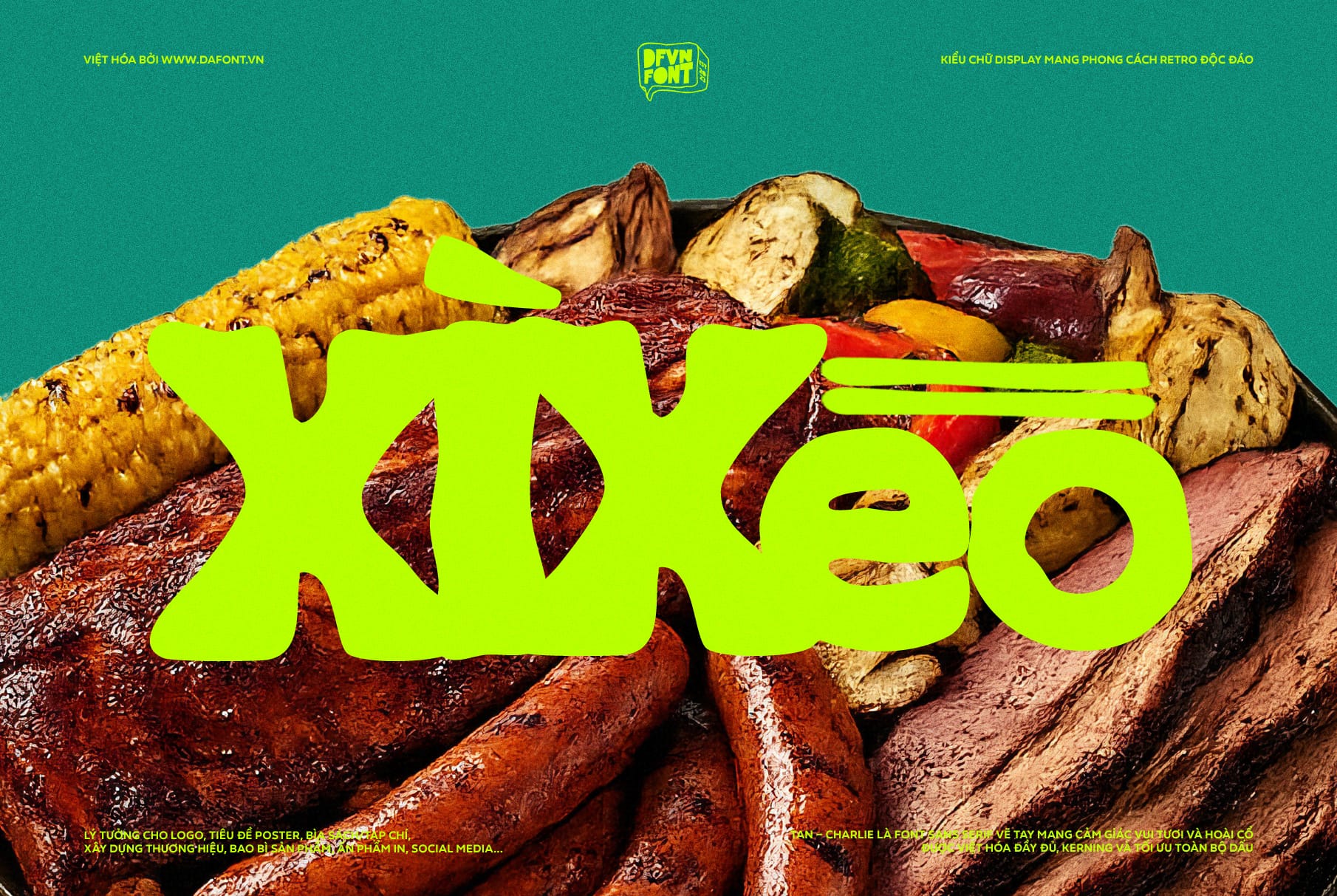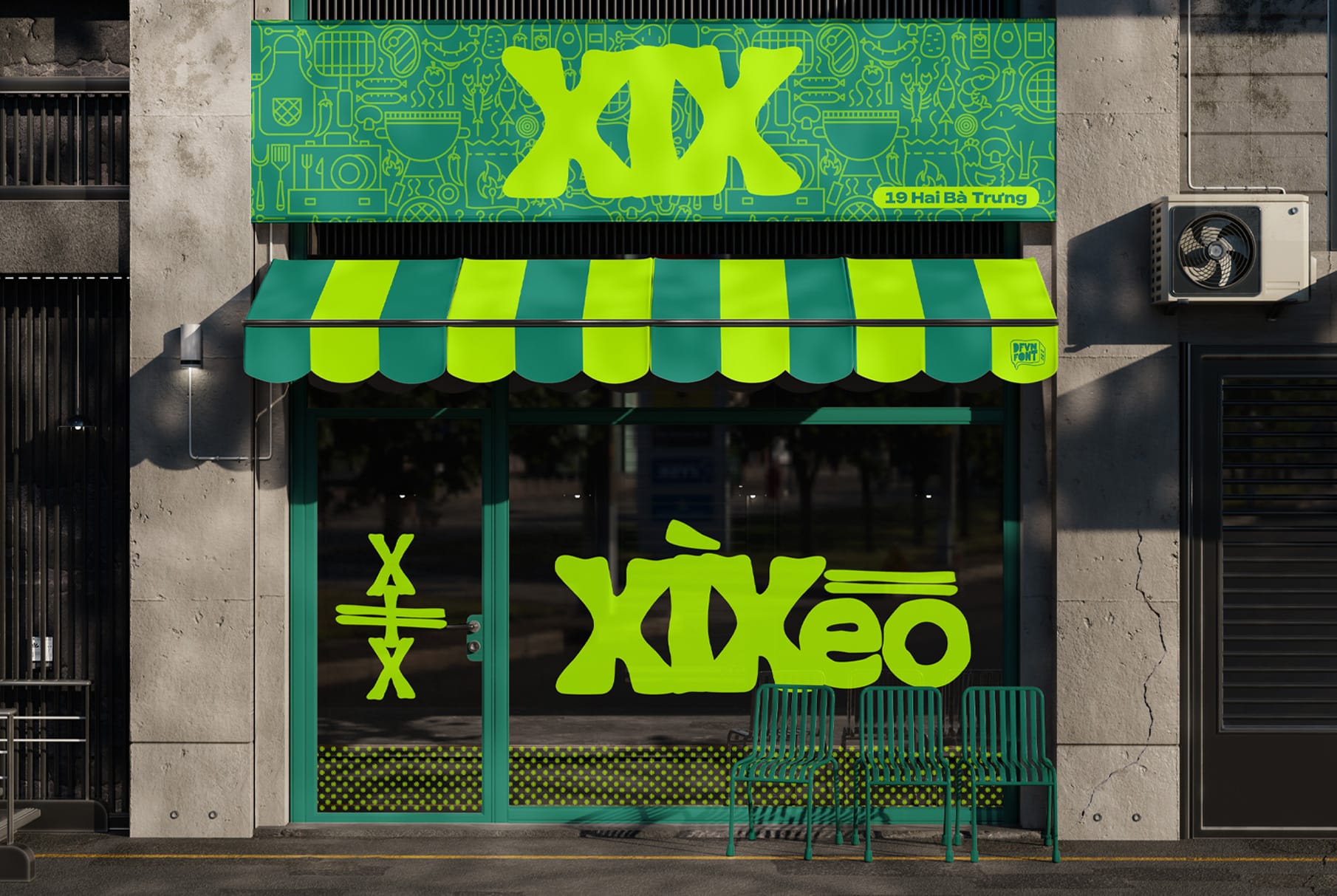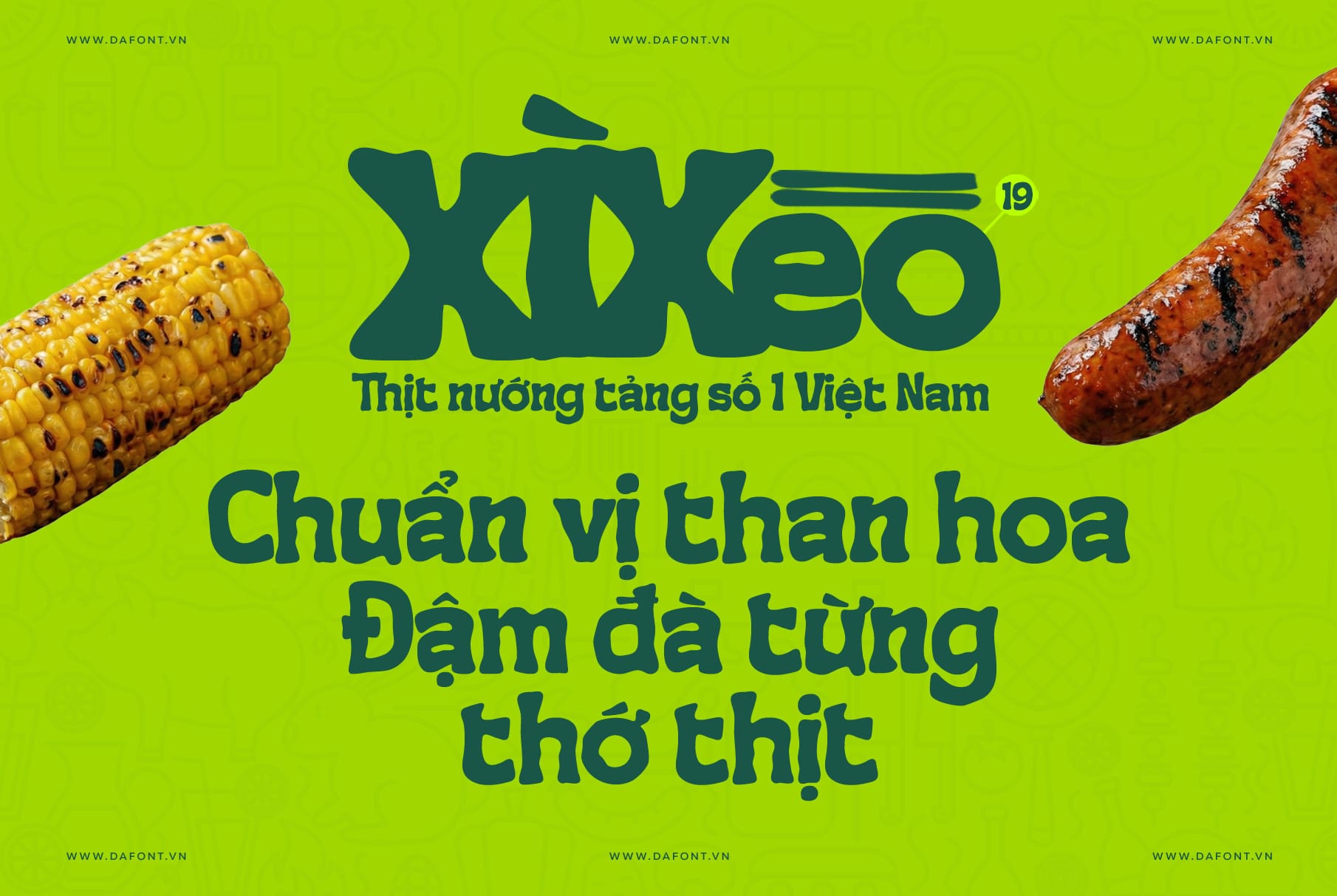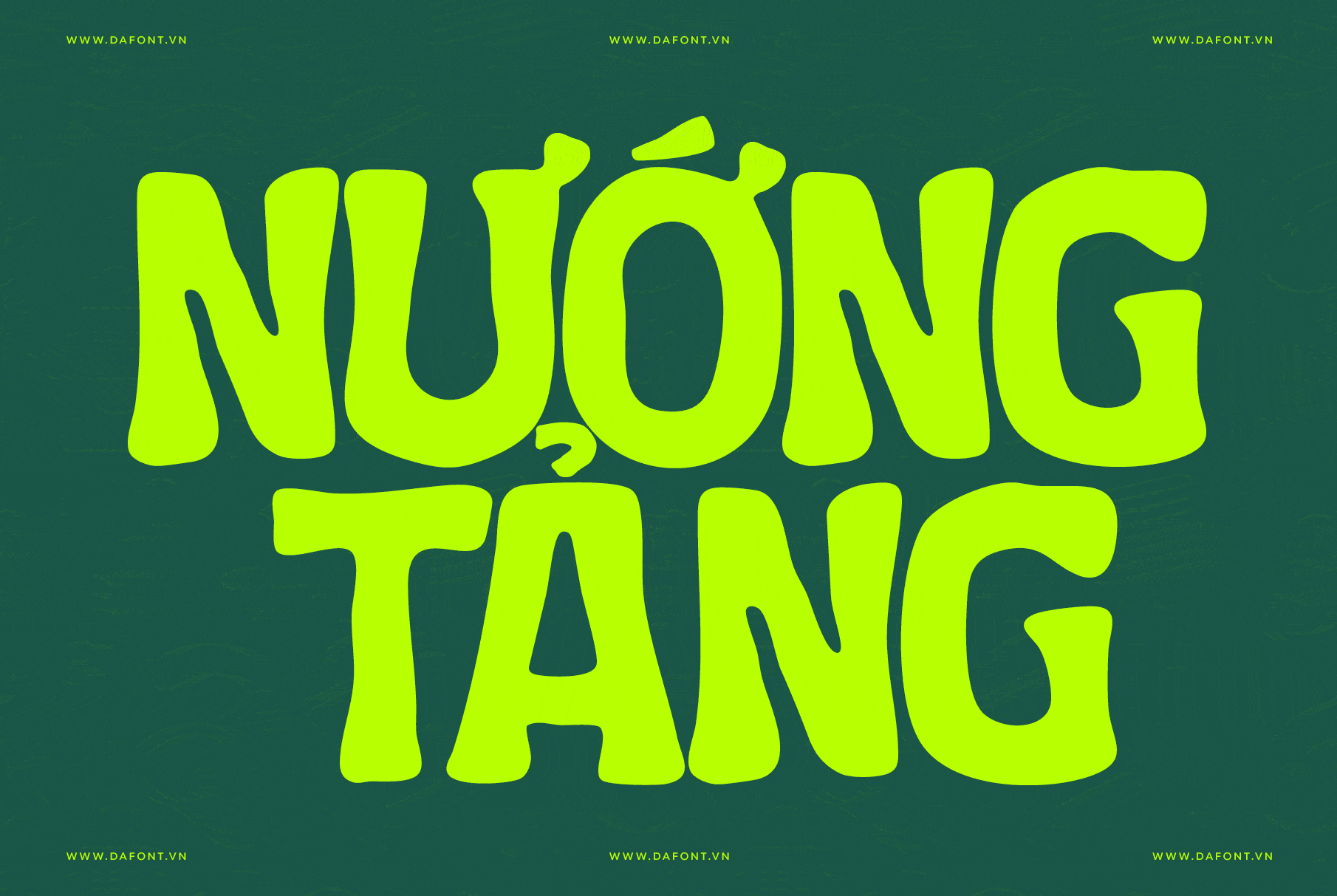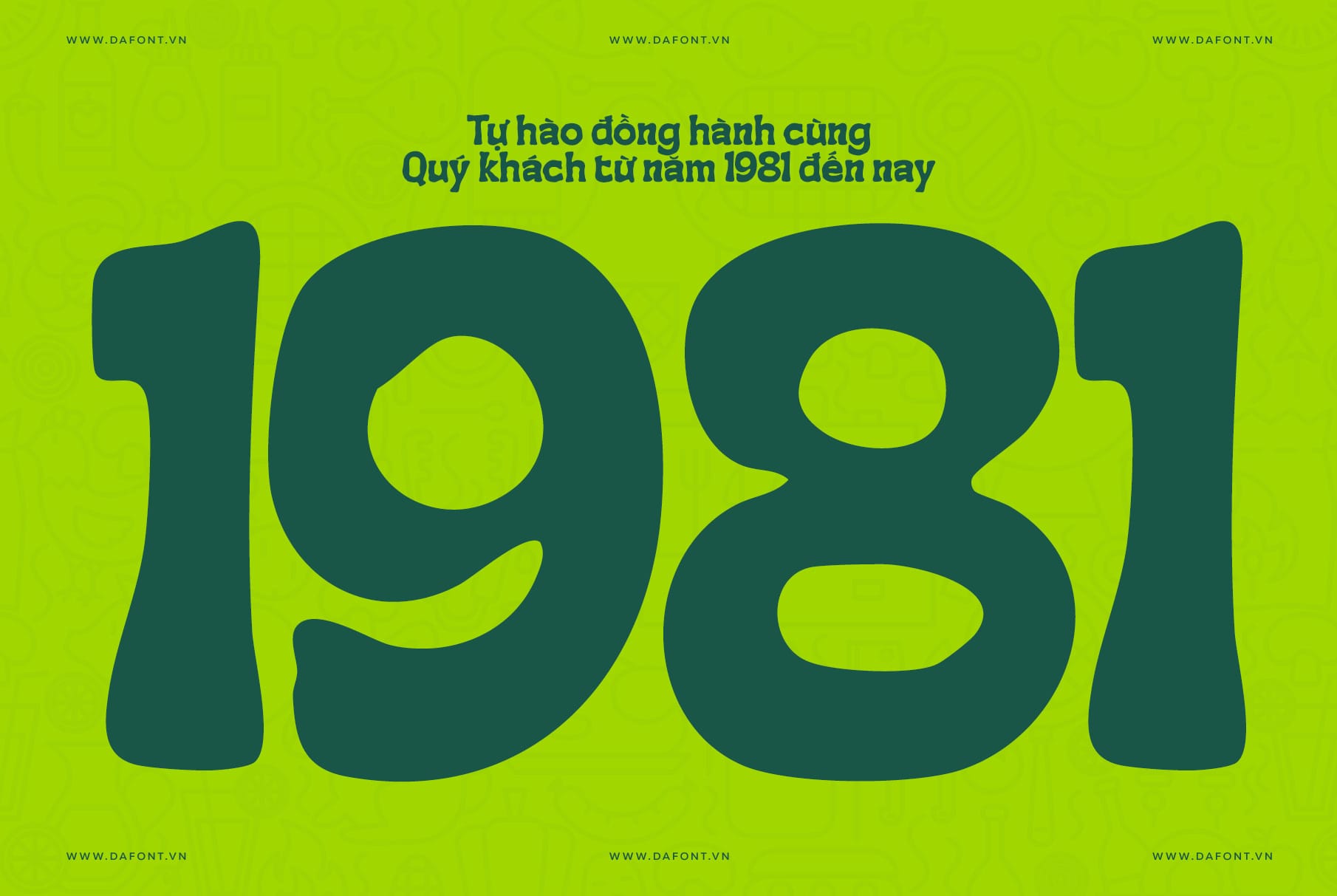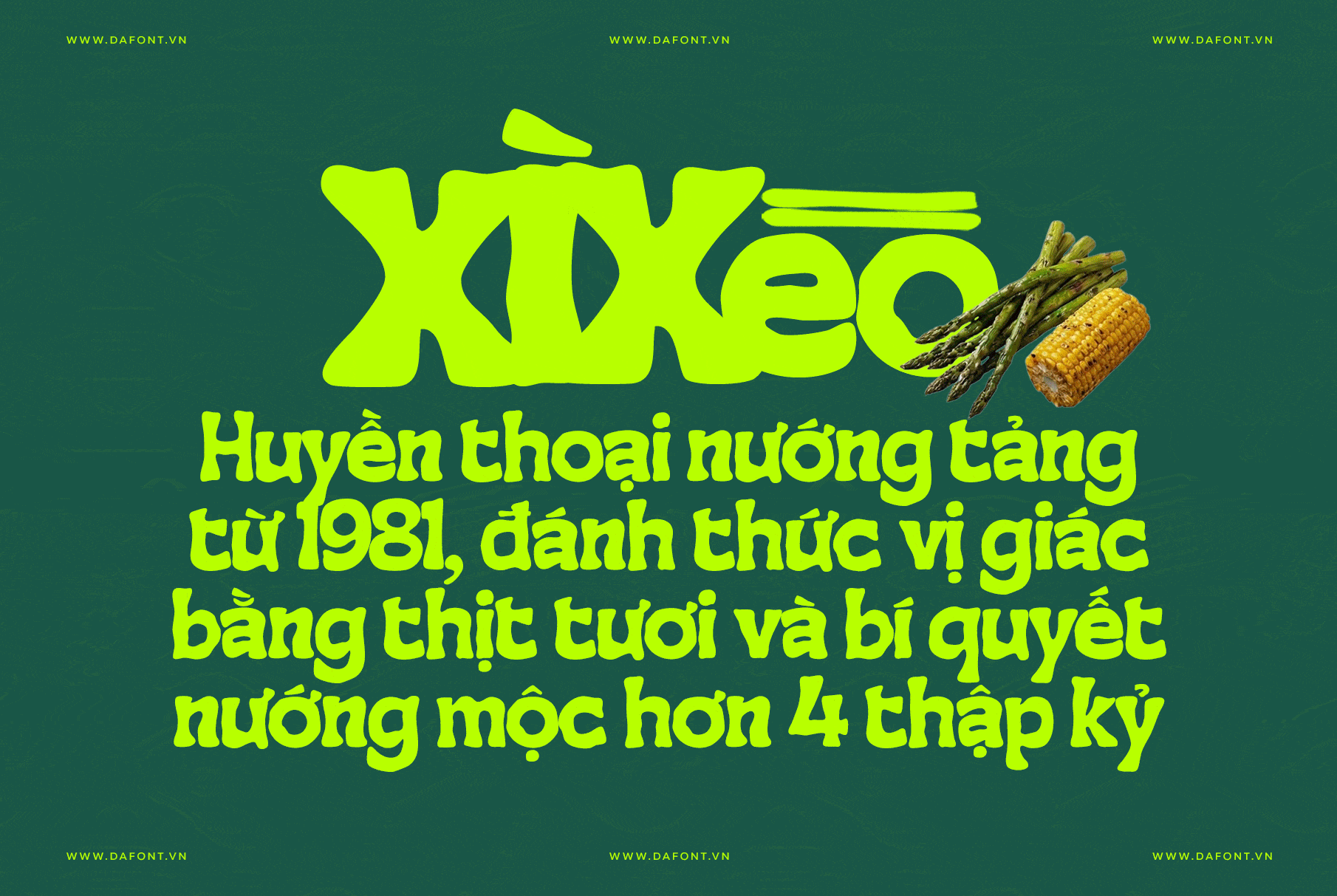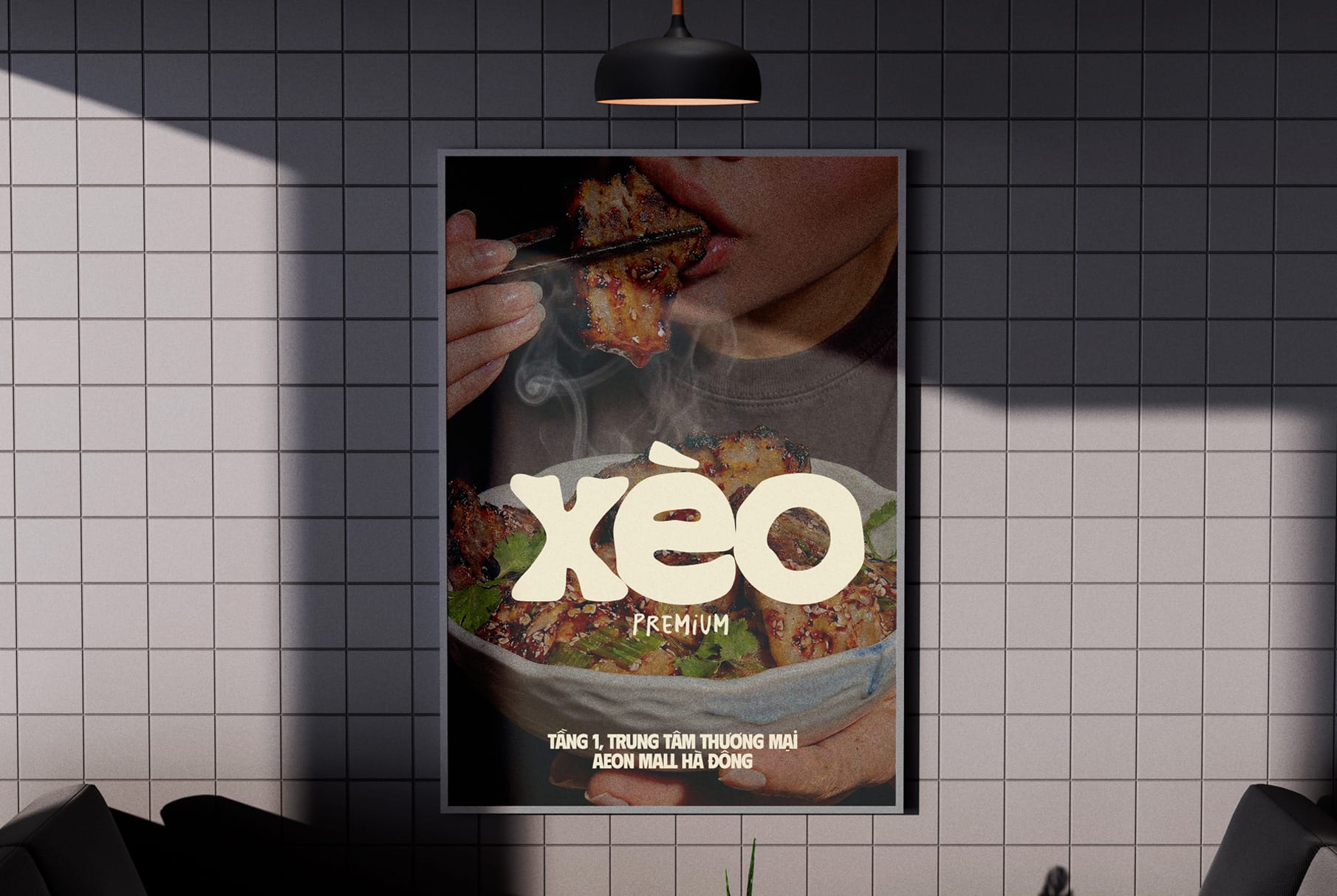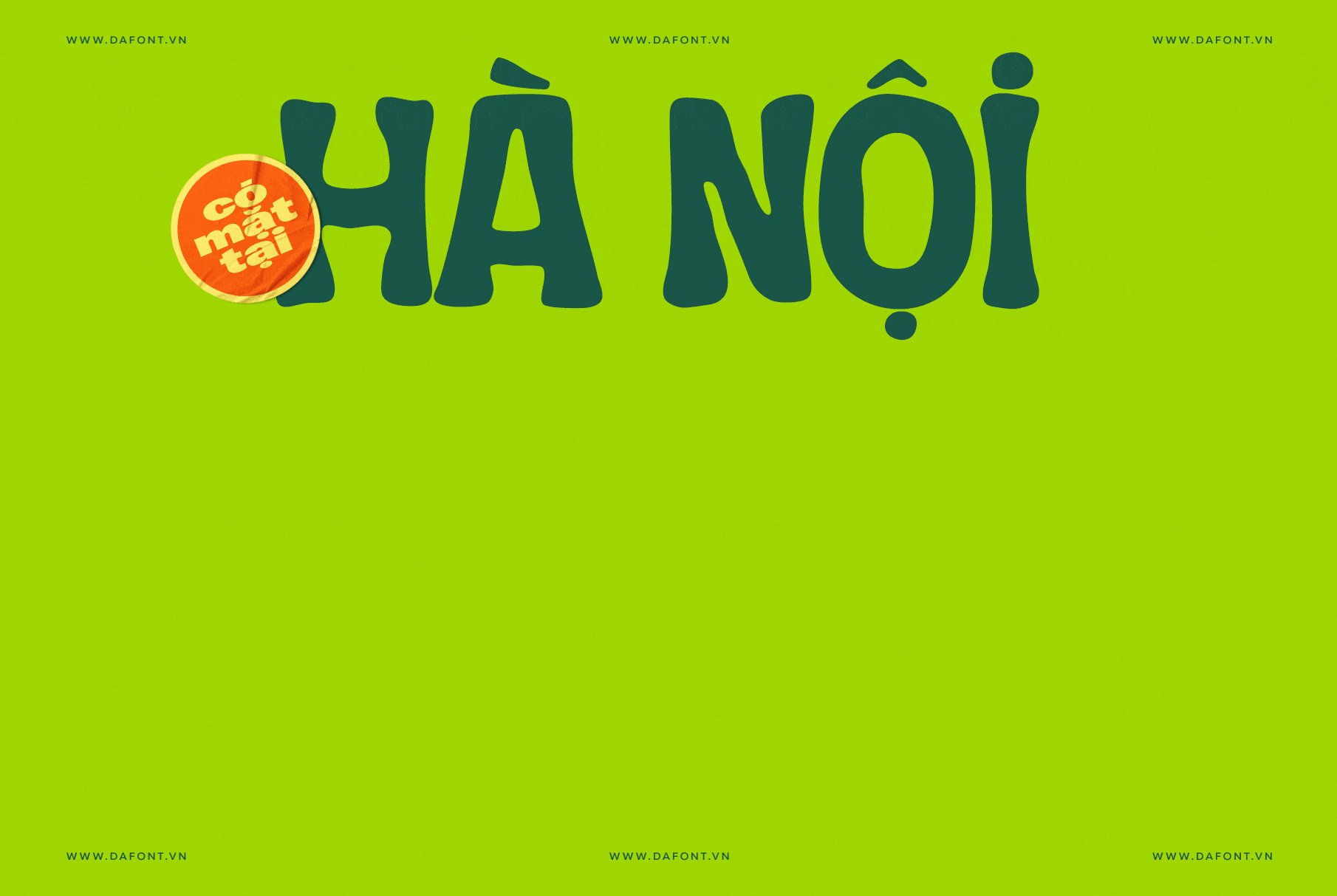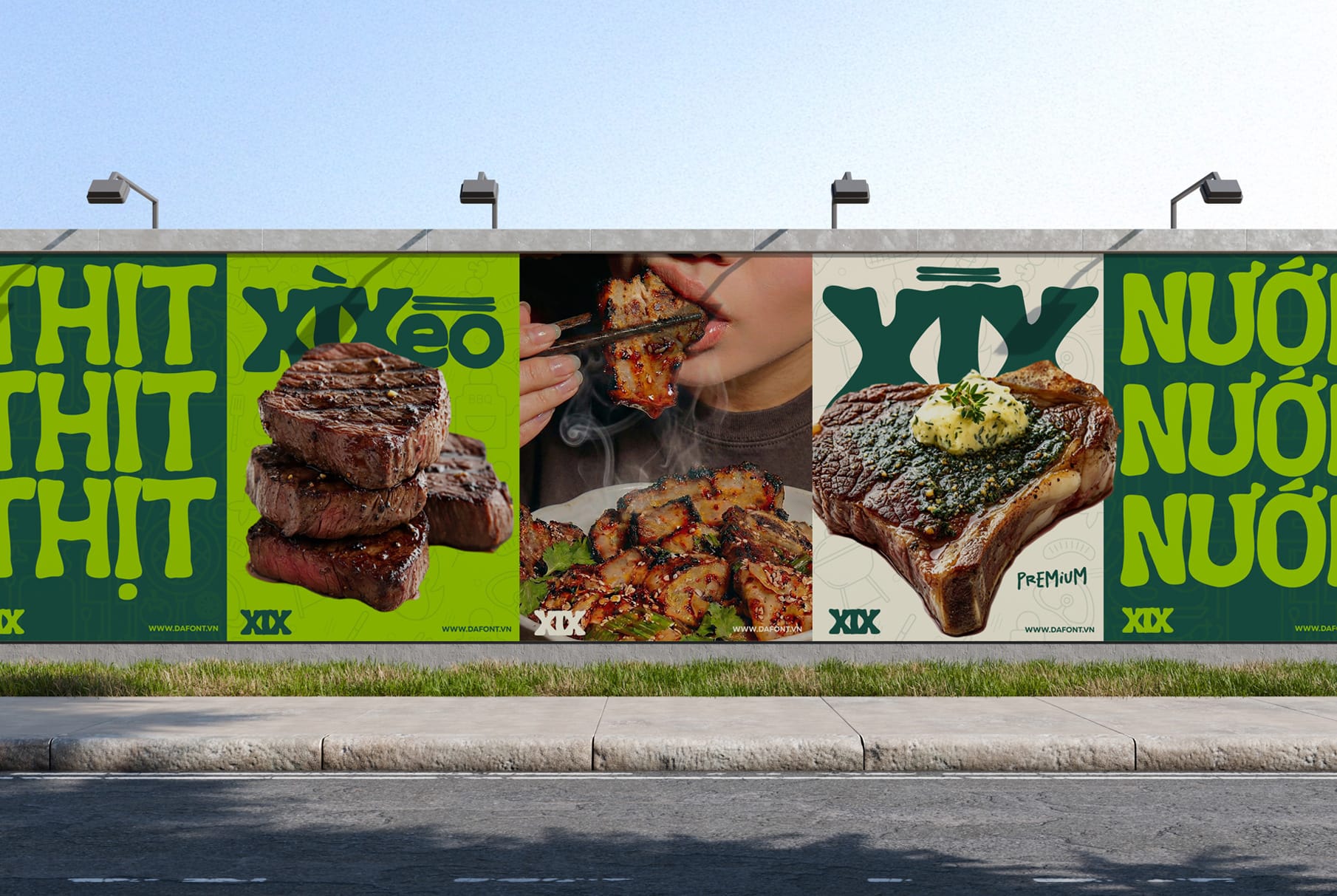
Trong vài năm trở lại đây, các font handwritten, retro và mang hơi hướng thủ công đang trở lại cực kỳ mạnh mẽ trong thiết kế thương hiệu. Giữa “rừng” font chữ đó, DFVN TAN – CHARLIE nổi bật như một lựa chọn độc đáo: vừa vui tươi, ấm áp, lại vừa hoài cổ nhưng không hề cũ kỹ.
Các đường nét của TAN – CHARLIE được thiết kế có chủ ý hơi lệch, không đồng đều như các font sans serif hiện đại. Chính cảm giác “không hoàn hảo” này tạo ra sự thủ công độc đáo, khiến text nhìn như được ai đó vẽ tay nhưng vẫn đủ chuyên nghiệp để đưa vào hầu hết các thiết kế.
Đặc điểm nổi bật DFVN TAN – CHARLIE
Tại sao TAN – CHARLIE lại được yêu thích đến vậy? Dưới đây là những lý do khiến font chữ này trở nên đặc biệt:
Đường nét vẽ tay tinh tế
TAN – CHARLIE không phải kiểu “chữ viết tay cẩu thả”, mà là hand-drawn sans serif có kiểm soát. Mỗi chữ cái đều được cân chỉnh về rhythm, weight và khoảng cách, đảm bảo khi ghép thành từ/ câu vẫn giữ được nhịp điệu thị giác dễ chịu.
- Nét chữ hơi bo tròn, không quá sắc cạnh
- Độ dày nét ổn định, dễ đọc khi dùng làm tiêu đề
- Tạo cảm giác thân thiện, gần gũi, rất hợp với các thương hiệu “human-centric”, brand, lifestyle, café, bakery, F&B,…
Mang phong cách retro nhưng vẫn hiện đại
Mặc dù DFVN TAN – CHARLIE mang phong cách retro, tuy nhiên với các đường nét và cách xử lý hình khối khá hiện đại, không bị “cũ kỹ”.
- Gợi nhớ đến bảng hiệu, poster, bìa sách cũ
- Nhưng layout, cân bằng hình khối lại phù hợp với branding, social media, UI hình ảnh ngày nay
- Rất hợp với các style: vintage soft, retro trẻ trung, boho, organic, tropical,…
Tính ứng dụng cao trong thực tế
Nhờ cá tính riêng mà vẫn dễ đọc, DFVN TAN – CHARLIE rất linh hoạt:
- Logo & nhận diện thương hiệu
- Tiêu đề website, banner, hero image
- Bao bì sản phẩm, nhãn dán, hộp quà, túi xách
- Ấn phẩm in: poster, brochure, tạp chí, postcard
- Merchandise & quà tặng: áo, tote bag, sticker,…
- Hình ảnh mạng xã hội: Instagram, Facebook, Tiktok, Threads…
Nếu bạn đang cần một font vừa có cá tính riêng, vừa dễ ghép với các font sans serif hoặc serif khác, DFVN TAN – CHARLIE là lựa chọn rất ổn.
Gợi ý cách dùng DFVN TAN – CHARLIE trong thiết kế
TAN – CHARLIE cực kỳ lý tưởng để dùng làm logo, tiêu đề poster, bao bì sản phẩm và hình ảnh mạng xã hội nhờ nét chữ vẽ tay mềm mại, hoài cổ nhưng vẫn hiện đại. Bạn có thể dùng font này cho brand café, bakery, thời trang, décor, lifestyle hoặc các thiết kế mang vibe vintage/organic, rồi kết hợp với một font sans/serif khác cho phần nội dung để tổng thể vừa nổi bật, vừa dễ đọc.
Kết luận
DFVN TAN – CHARLIE là một trong những font hand-drawn sans serif hiếm hoi vừa giữ được cảm xúc thủ công, vừa đạt chất lượng đủ “premium” để sử dụng trong các dự án thiết kế thương hiệu, cả online lẫn offline.
Nếu bạn đang xây dựng một brand mang màu sắc tự nhiên, ấm áp, retro nhưng vẫn tinh tế và hiện đại, hãy thử đưa TAN – CHARLIE vào hệ thống font của mình – rất có thể đây sẽ là “nhân vật chính” mới trong kho font yêu thích của bạn.